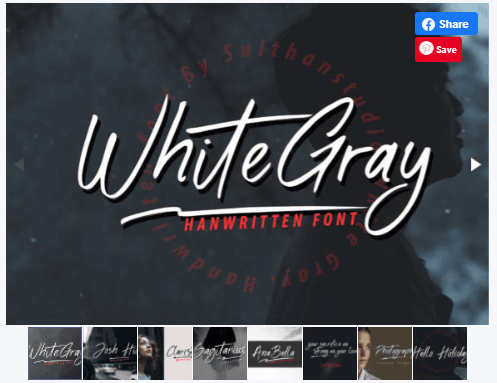
White Gray Font
White Grey - стильный и нежный шрифт. У него чистая, тонкая и гладкая атмосфера, и он станет хитом для любого дизайна, к которому вы хотите добавить его. Этот шрифт имеет кодировку PUA, что означает, что вы можете легко получить доступ ко всем глифам и росчеркам!